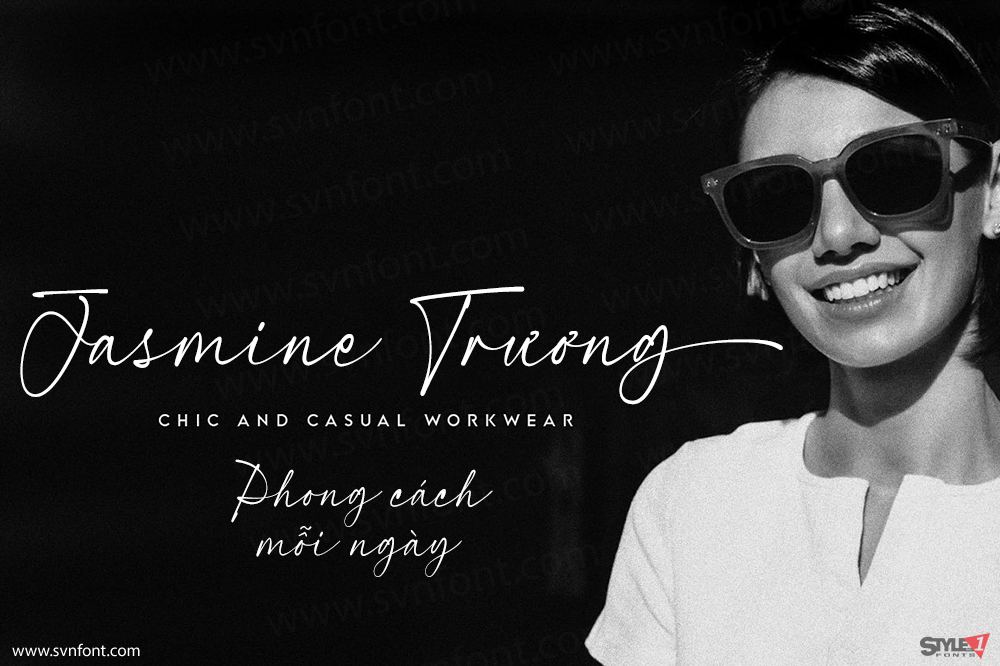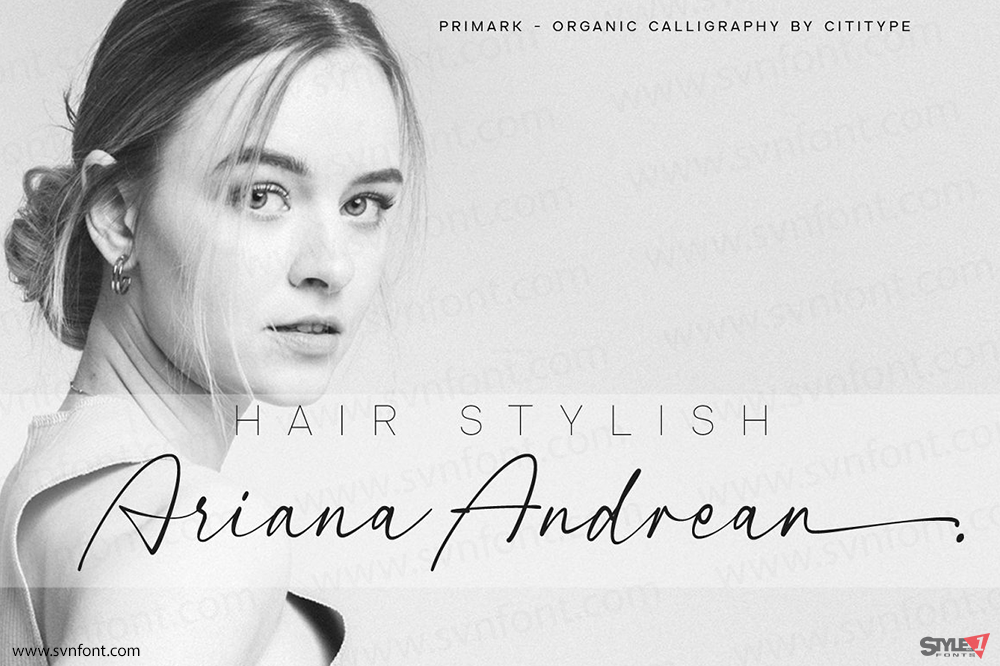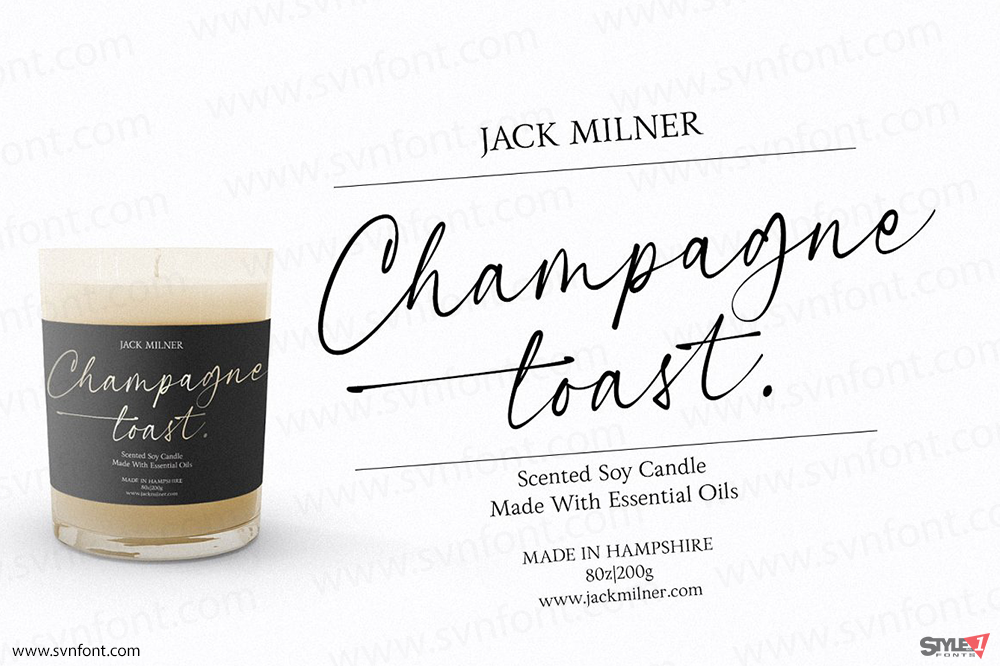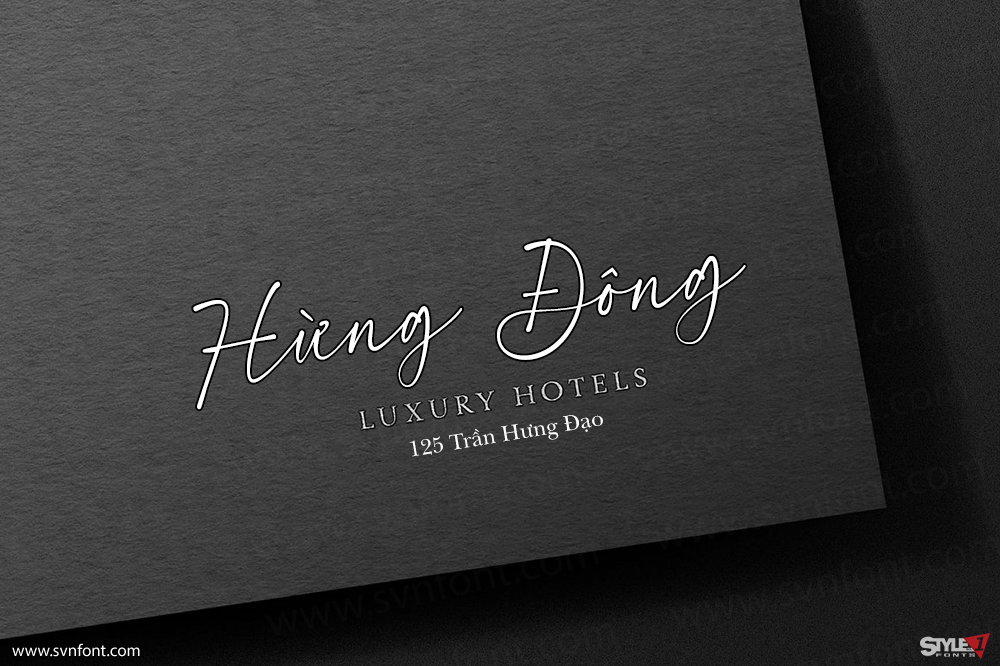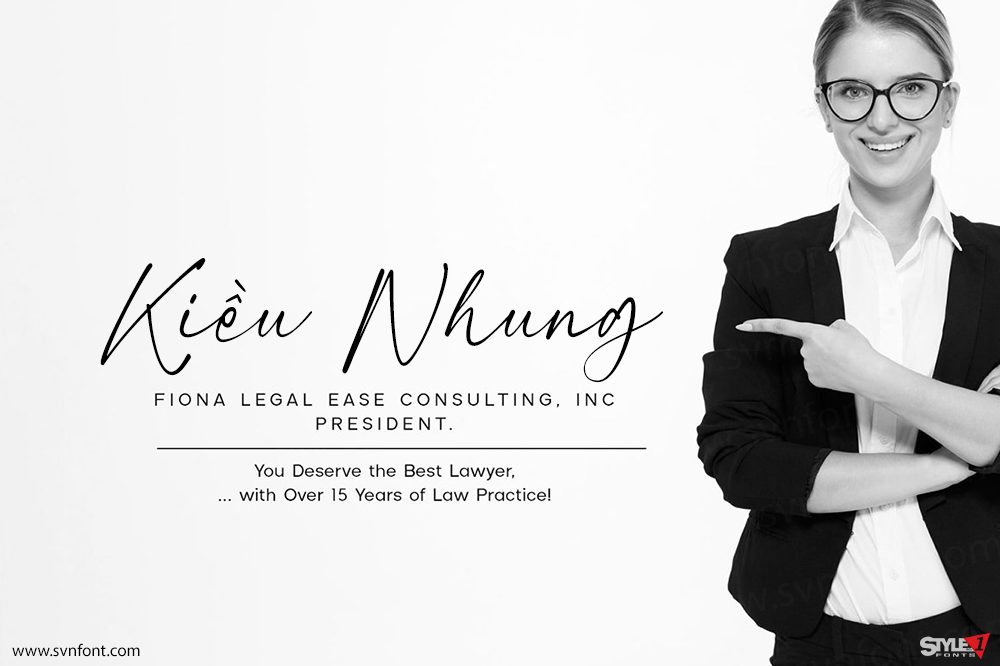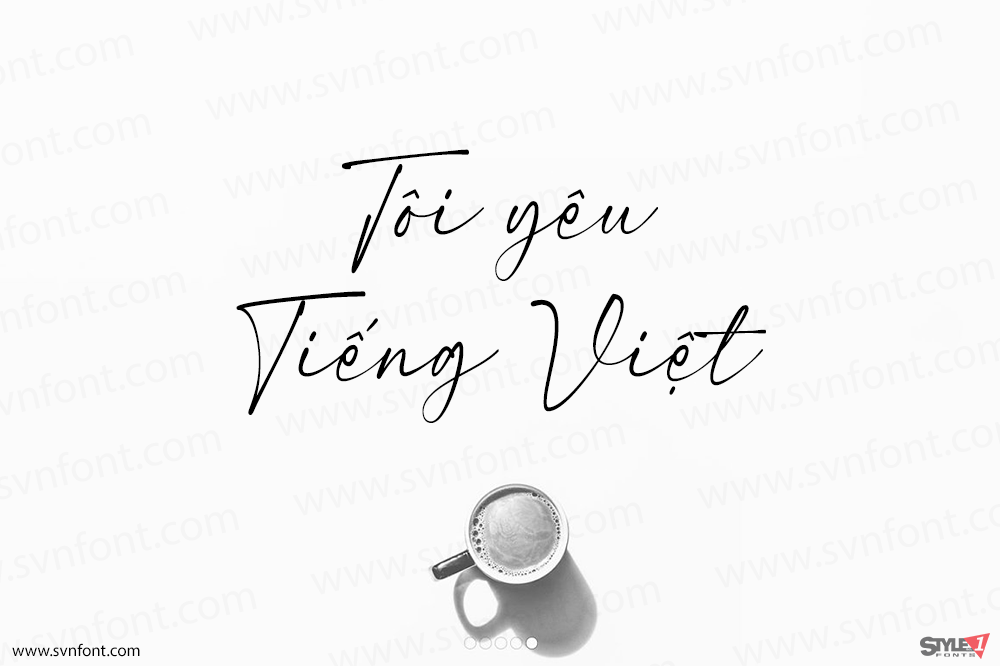
Primark là một phông chữ script sang trọng, hiện đại và thanh lịch với vẻ ngoài nổi bật, đây là một lựa chọn tuyệt vời cho logo, tên thương hiệu, chữ ký số, hồ sơ trực tuyến, banner trang web, áp phích, thiệp mời đám cưới, tiêu đề sách và các tiêu đề. Phông chữ Primark bao gồm 3 kiểu: Primark Regular (thường), Alternate (thay thế) và Swash (nét trang trí). Chúng được thiết kế theo cùng một hệ thống đo lường để có thể kết hợp với nhau.
Đi kèm với các chữ ghép (ligature) để tạo ấn tượng tự nhiên hơn và được hỗ trợ dấu phụ cho nhiều ngôn ngữ khác nhau. Sang trọng, hiện đại, thanh lịch và nổi bật là những từ có thể mô tả định nghĩa của phông chữ này.
Nhà thiết kế: Cititype
Nhà phát hành: Cititype